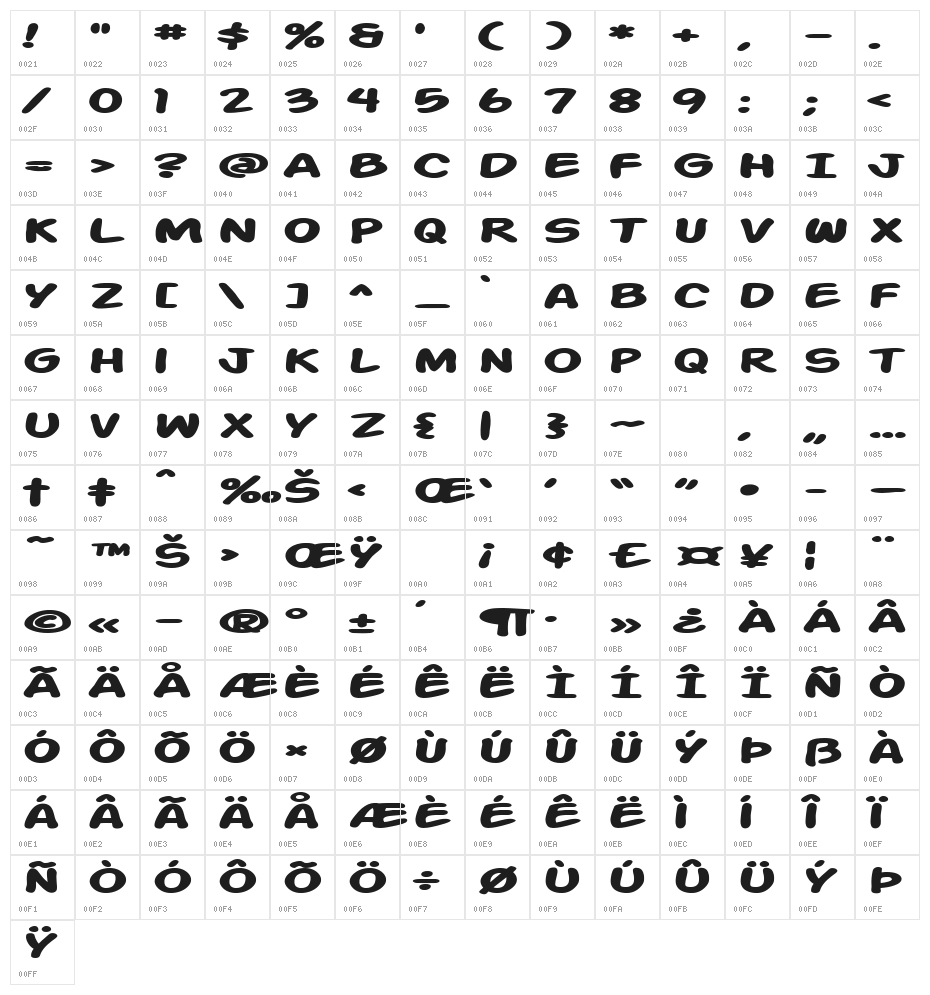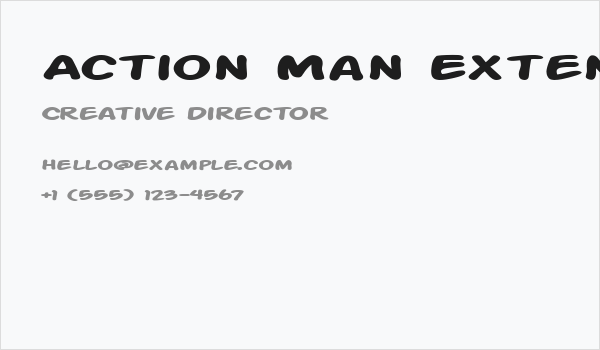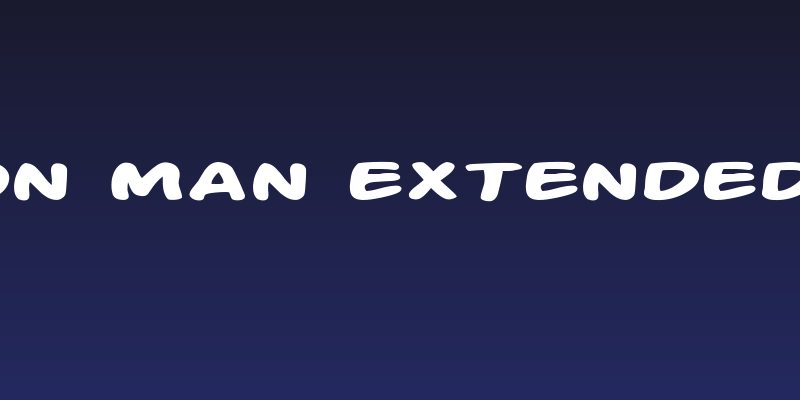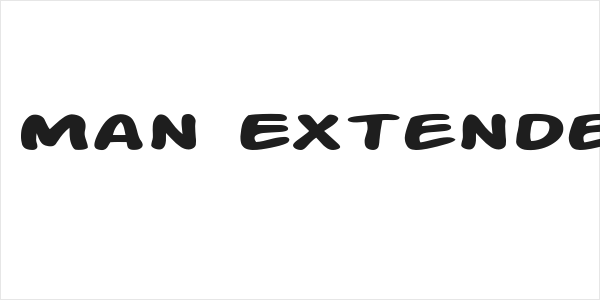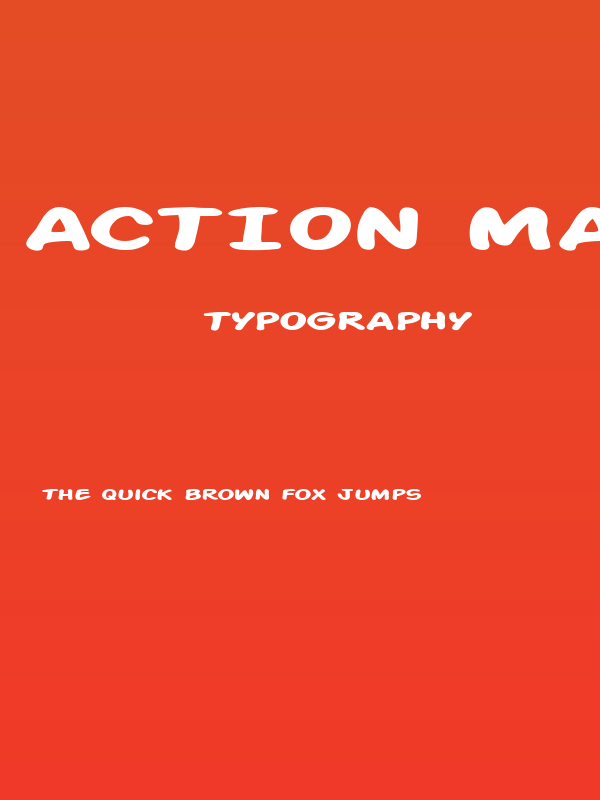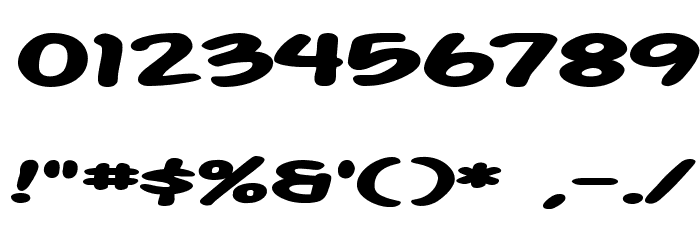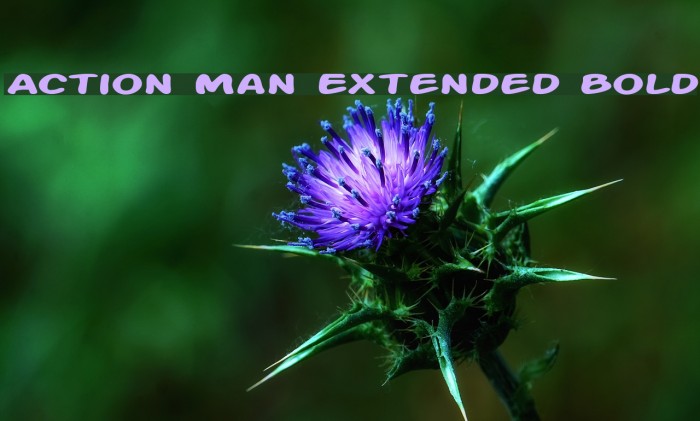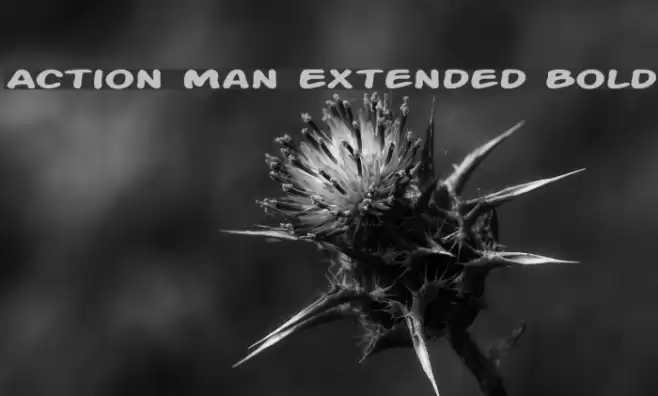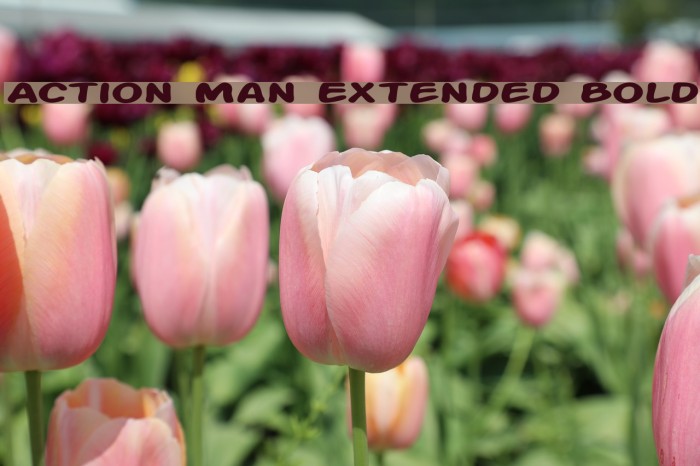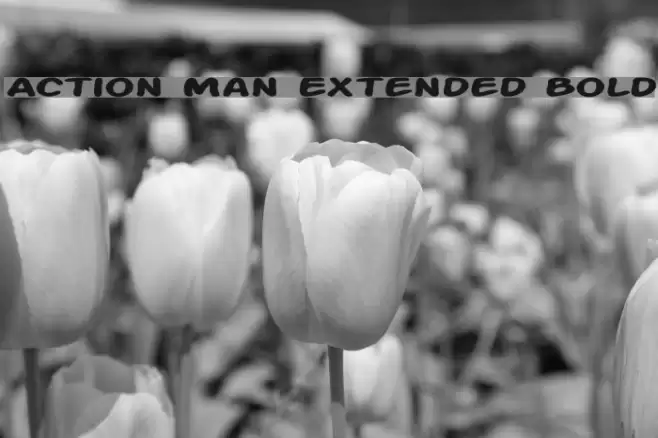
Action Man Extended Bold Font
| Style général | Playful, Informal |
| Cas d'utilisation | Headlines, Posters, Branding |
| Projets proposés | Perfect for children's books, playful branding, posters, and casual invitations. |